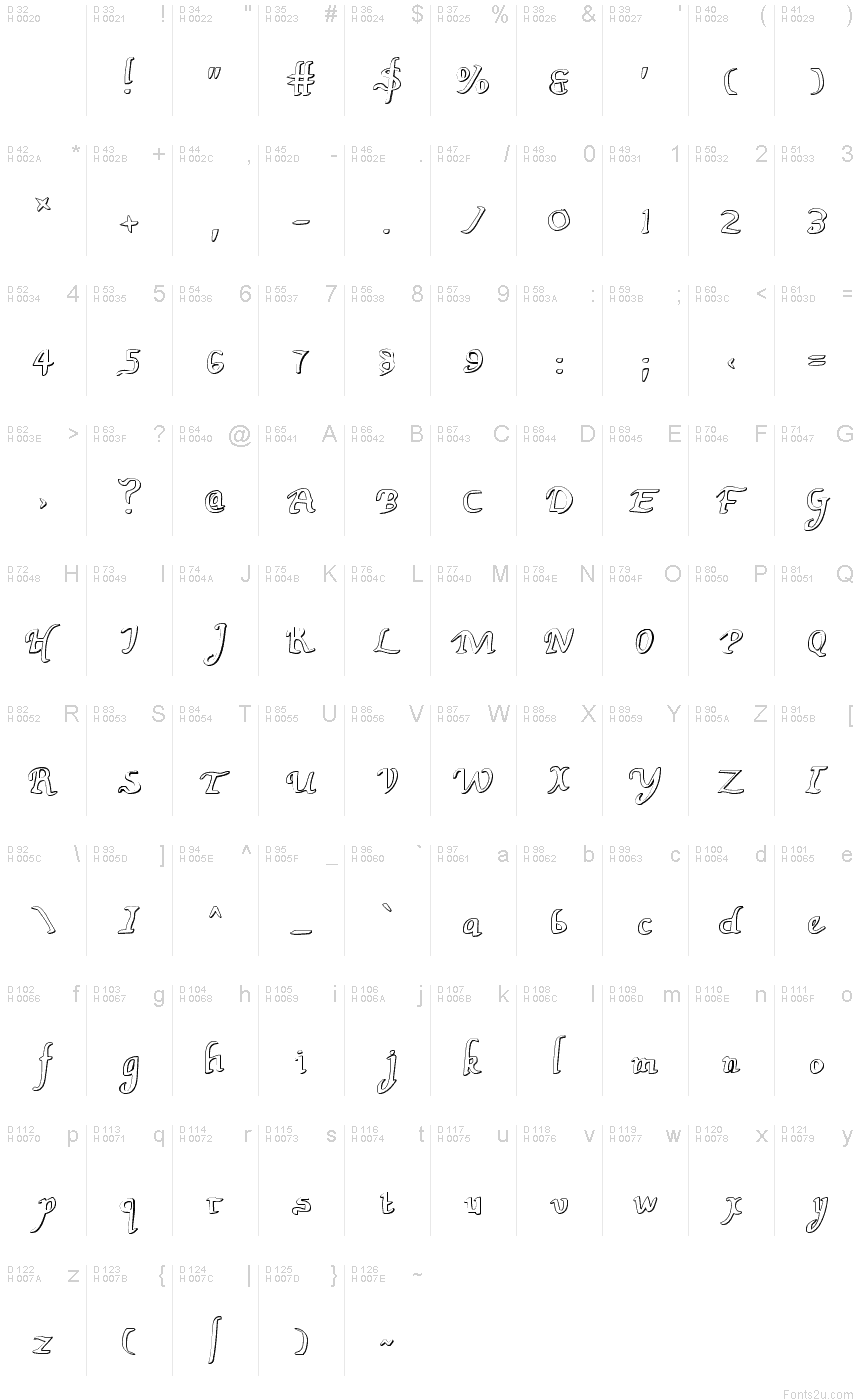
Valley Forge Outline autorstwa Iconian Fonts to darmowy, konturowy krój pisma ekspozycyjnego z wysokimi, pochylonymi w prawo literami i swobodnym, kaligraficznym rozmachem. Jego podwójne kontury, zwężające się łuki i ostre dolne punkty nadają napisom żywą, odręcznie rysowaną sylwetkę.
Otwarte wnętrza pasują do plakatów retro, opraw muzycznych, grafik imprezowych i swobodnej odzieży, gdzie linie mogą pozostać aktywną częścią projektu. Używaj go w dużych rozmiarach i unikaj przeładowanych teł, ponieważ wąskie przerwy między wewnętrznymi a zewnętrznymi kreskami mają kluczowe znaczenie dla jego wyglądu.